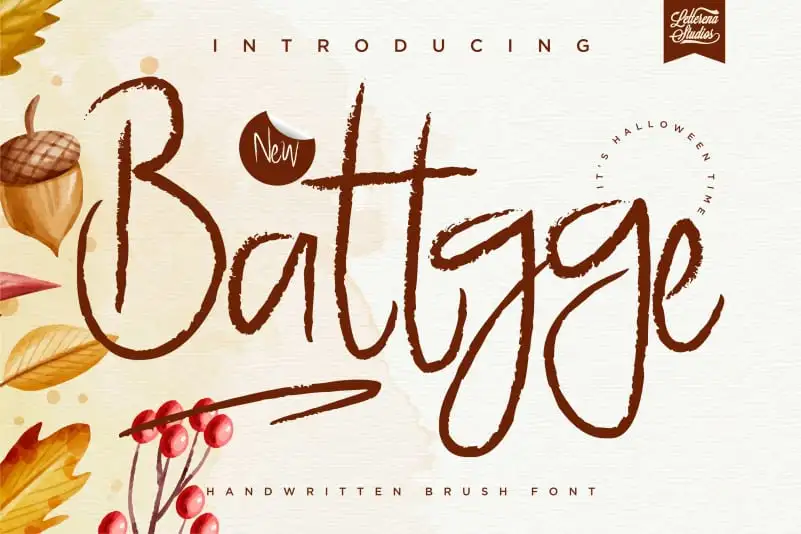
Battgge Brush Font – Download Grátis
A Battgge Brush Font é uma escolha perfeita para designers que buscam adicionar um toque elegante e sofisticado a seus projetos digitais. Inspirada no estilo das canetas cursivas, essa fonte oferece linhas suaves e vibrantes que se adequam perfeitamente aos designs de marca, gráficos publicitários e até mesmo à criação de conteúdo online. Com letras expressivas e uma aparência fluida, a Battgge Brush Font é uma opção versátil para projetos que exigem um acabamento cuidadoso. Para designers atentos ao uso do material original da fonte, é importante ressaltar que esta fonte está disponível apenas sob o uso pessoal não comercial. Essa restrição garante sua exclusividade e valor adicional aos criadores de conteúdo, incentivando-os a experimentar novas formas de expressão visual sem preocupações financeiras. A Battgge Brush Font é uma escolha inteligente para quem busca um recurso gráfico que se destaca enquanto preserva o equilíbrio entre qualidade estética e responsabilidade ética.